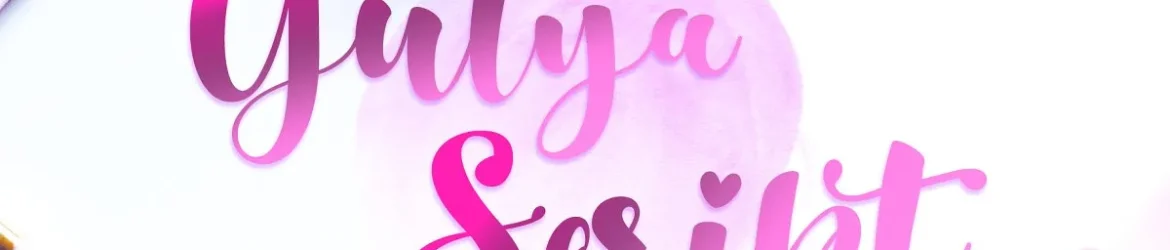
A Gulya Script Font é uma opção única para aqueles que desejam adicionar um toque autêntico e vintage a seus projetos digitais. Desenvolvida com amor pela designer 24Design, essa fonte de estilo script é perfeitamente adequada para criações como selos, logotipos, cartões de lembrança ou camisetas personalizadas. Suas linhas suaves e detalhes delicados fazem dela uma escolha ideal para aqueles que desejam um ar retrô em seus designs modernos. Ideal tanto para designers gráficos quanto para amadores apaixonados por arte, a Gulya Script pode ser utilizada com sucesso em projetos como selos de tatuagem, cartões de aniversário, camisetas customizadas e até mesmo na produção de mídia social. Suas características elegantes e delicadas permitem que você personalize seus designs de maneiras únicas, fazendo-a uma fonte versátil para uso em uma ampla variedade de aplicativos. Engane-se se pensasse que a Gulya Script é apenas uma fonte: ela pode transformar qualquer projeto em um elemento de design único e memorável.